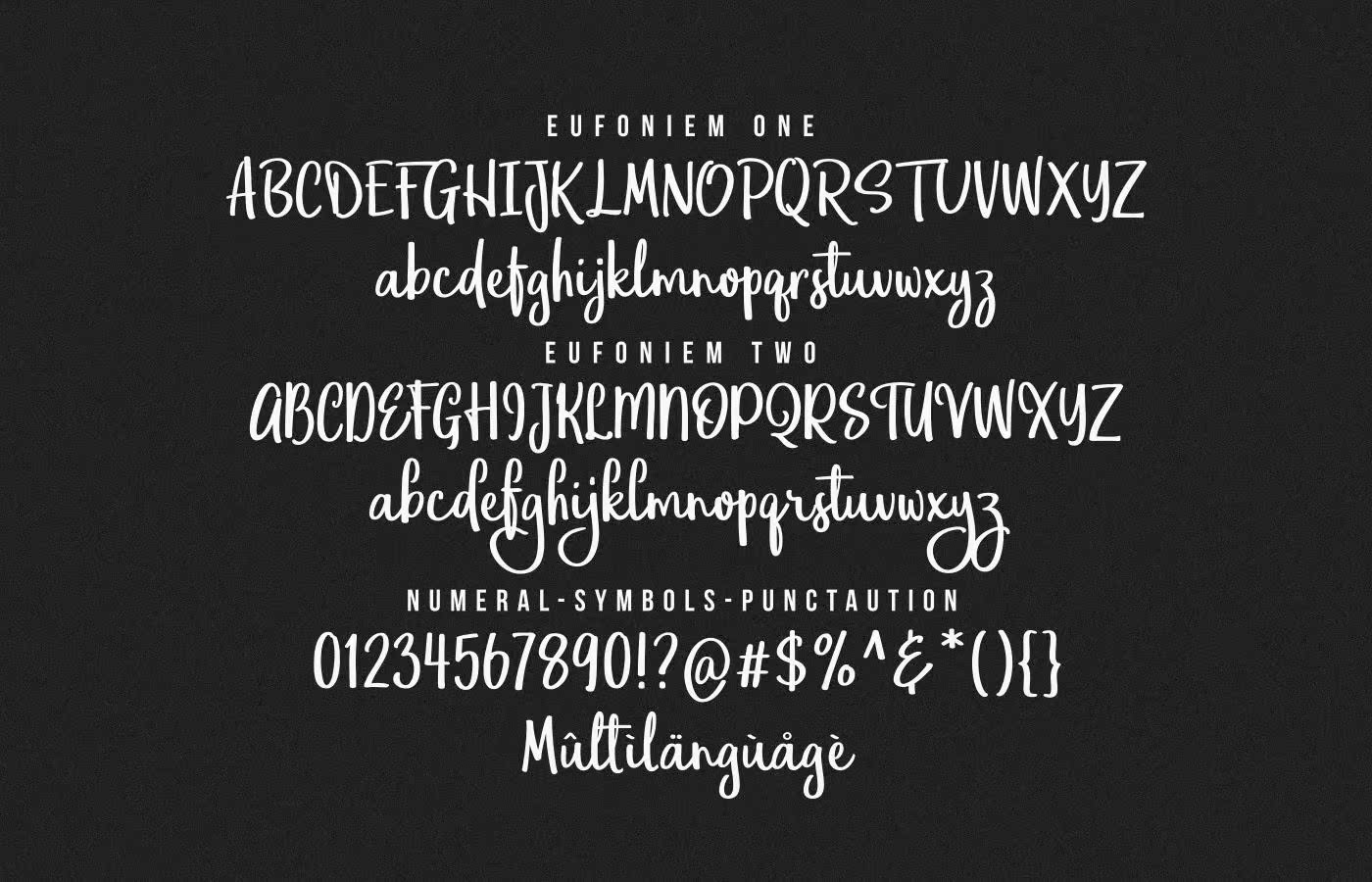
赫里蒂斯!最新的自定义类型来自Motomotype,Eufonie是Scriptfreefont。Eufonie是Uponiye和Euphonium结合的结果。Yuponiy是一个女人的名字,她聪明、性感、勇敢。她有强烈的声音反对父权制,但她也是女性生活中的一个始祖和优雅。她是哈佛历史中“RaraMendut”的现代形象。就像尤波尼姆一样,尤芬妮是一种活泼的字体,但不是女性化的,有些人不想代表她们的信息。尤芬妮也是从音乐乐器“euphonium”中产生的。它的风格和声音让尤芬妮充满个性。曲线性感,在和声中发出洪亮的声音。Eufonie包含两种变体;Eufonie Mone和UFONIEM两款。因此,您可以轻松地混合和匹配您的字体和设计,使其更加多样化。此外,此款字体100%免费供个人和商业使用。